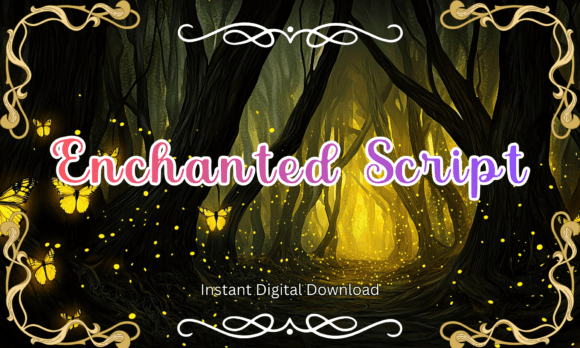
Enchanted Script
Enchanted Scriptのような高品質の素材をお探しの場合、このプレミアムパッケージはクリエイティブなプロジェクトに素晴らしい選択です。
POD(オンデマンド印刷)製品、結婚式の招待状、またはソーシャルメディアのグラフィックを作成している場合でも、Enchanted Scriptは理想的です。